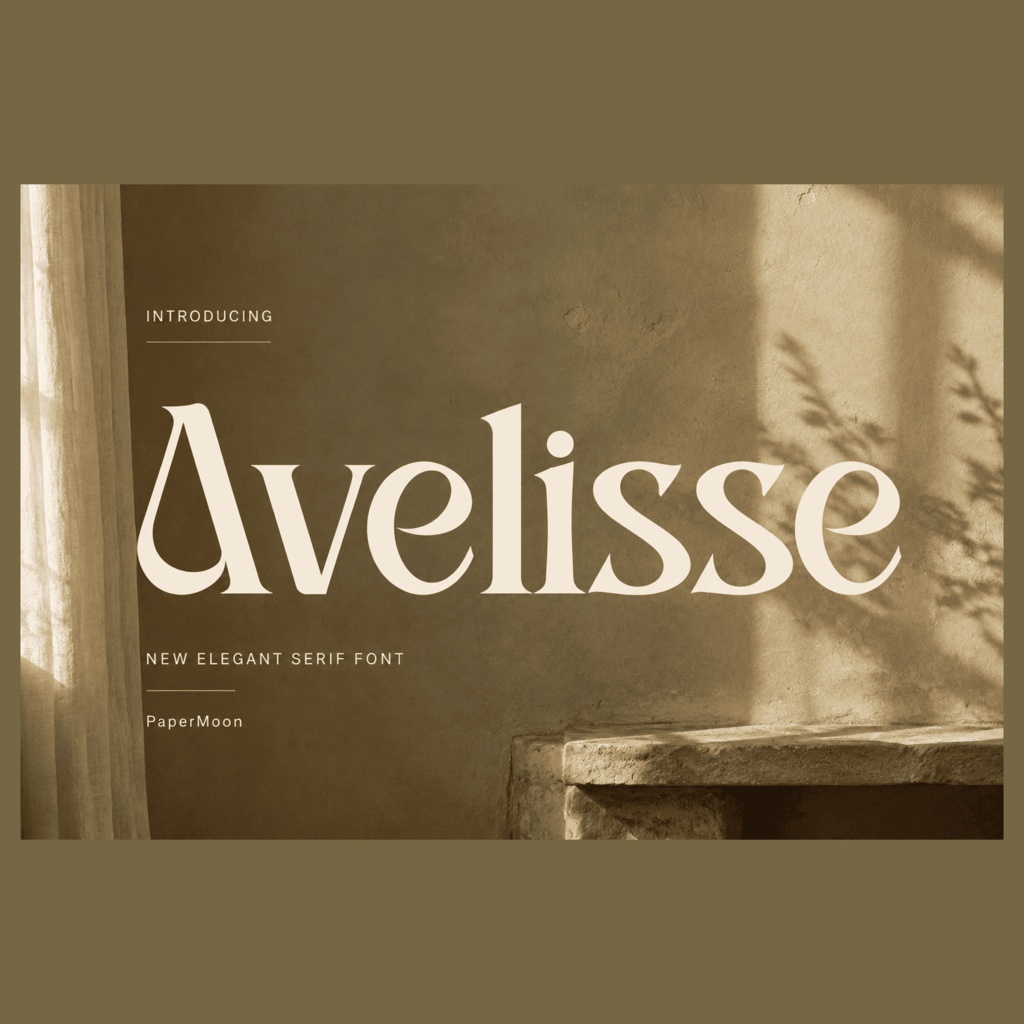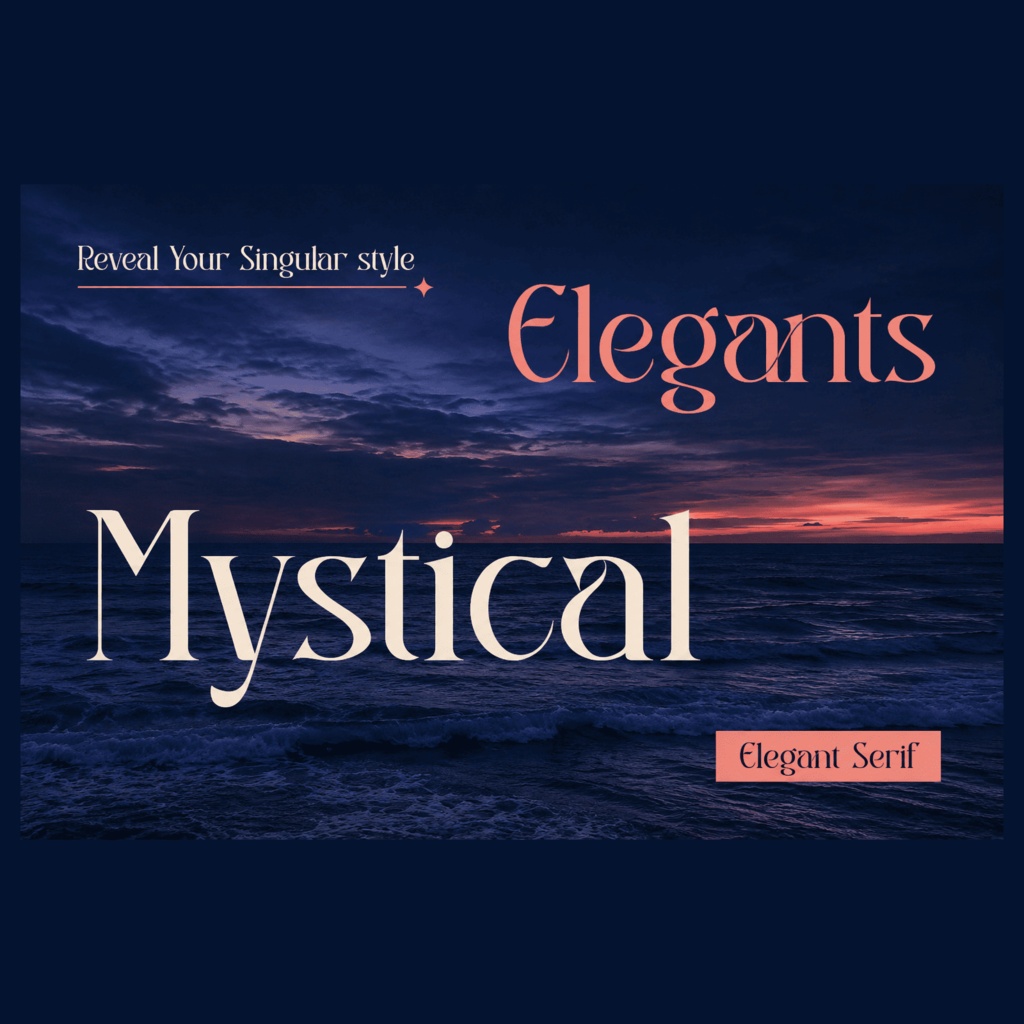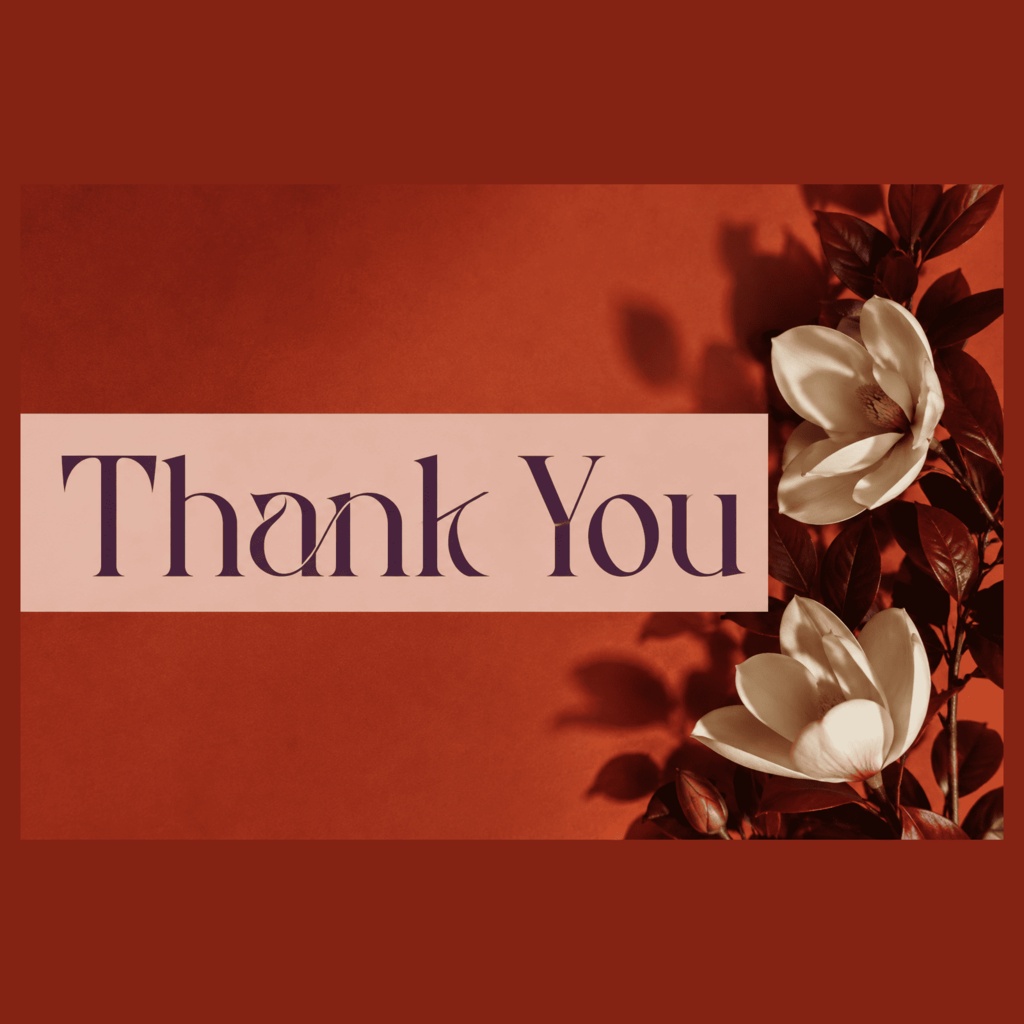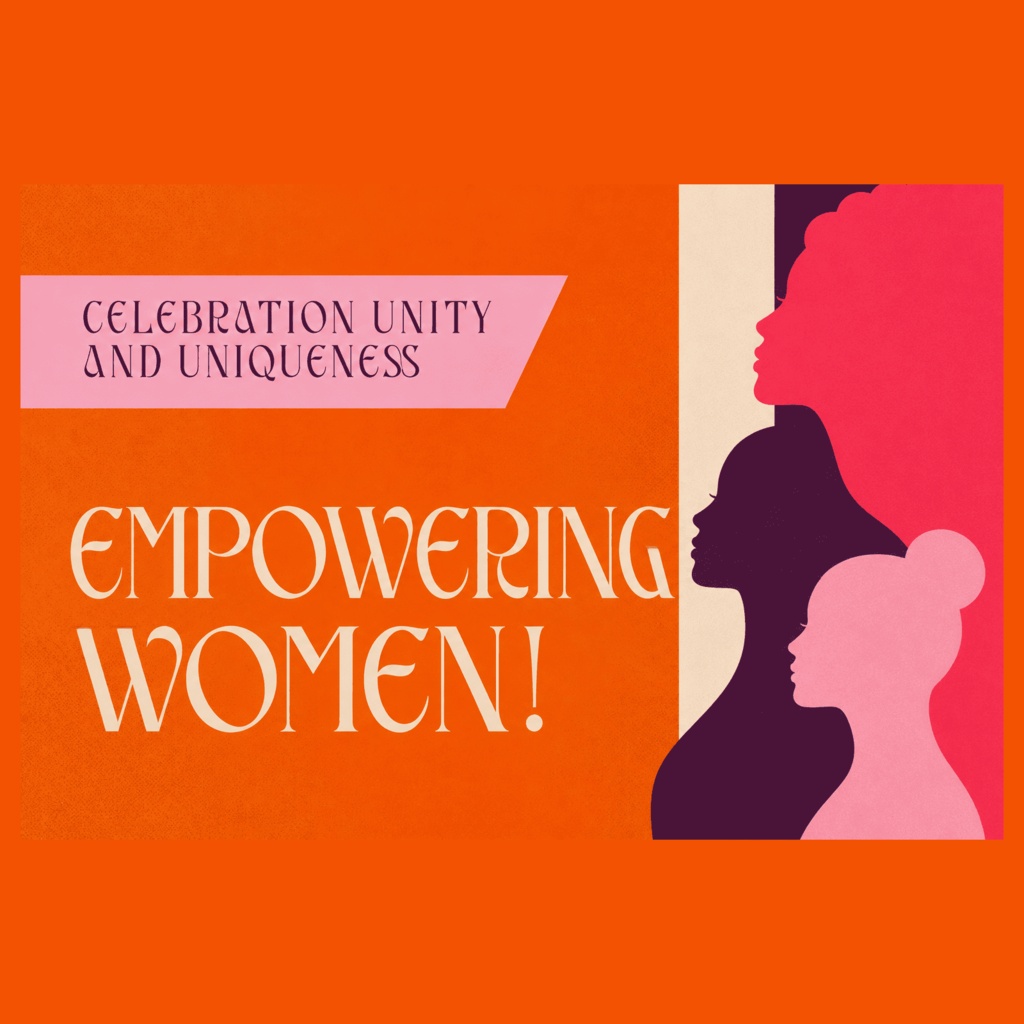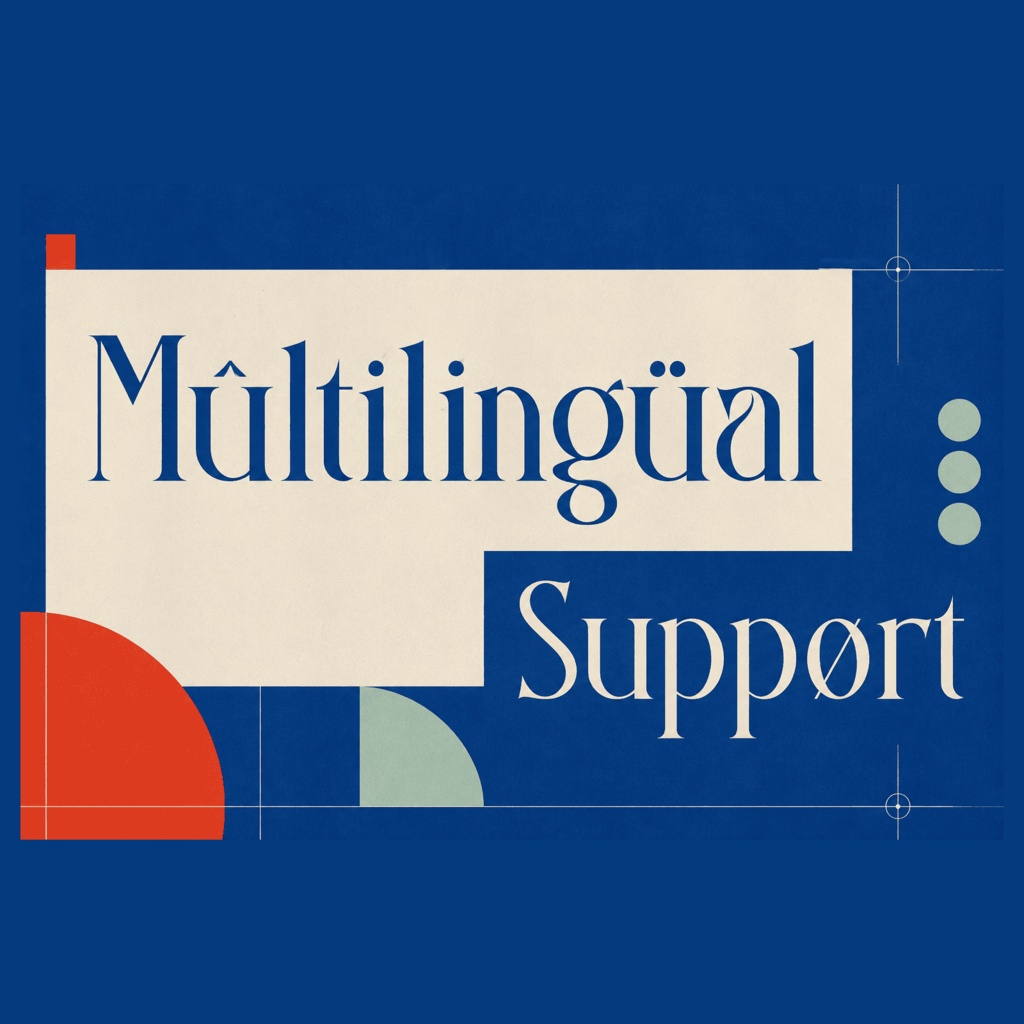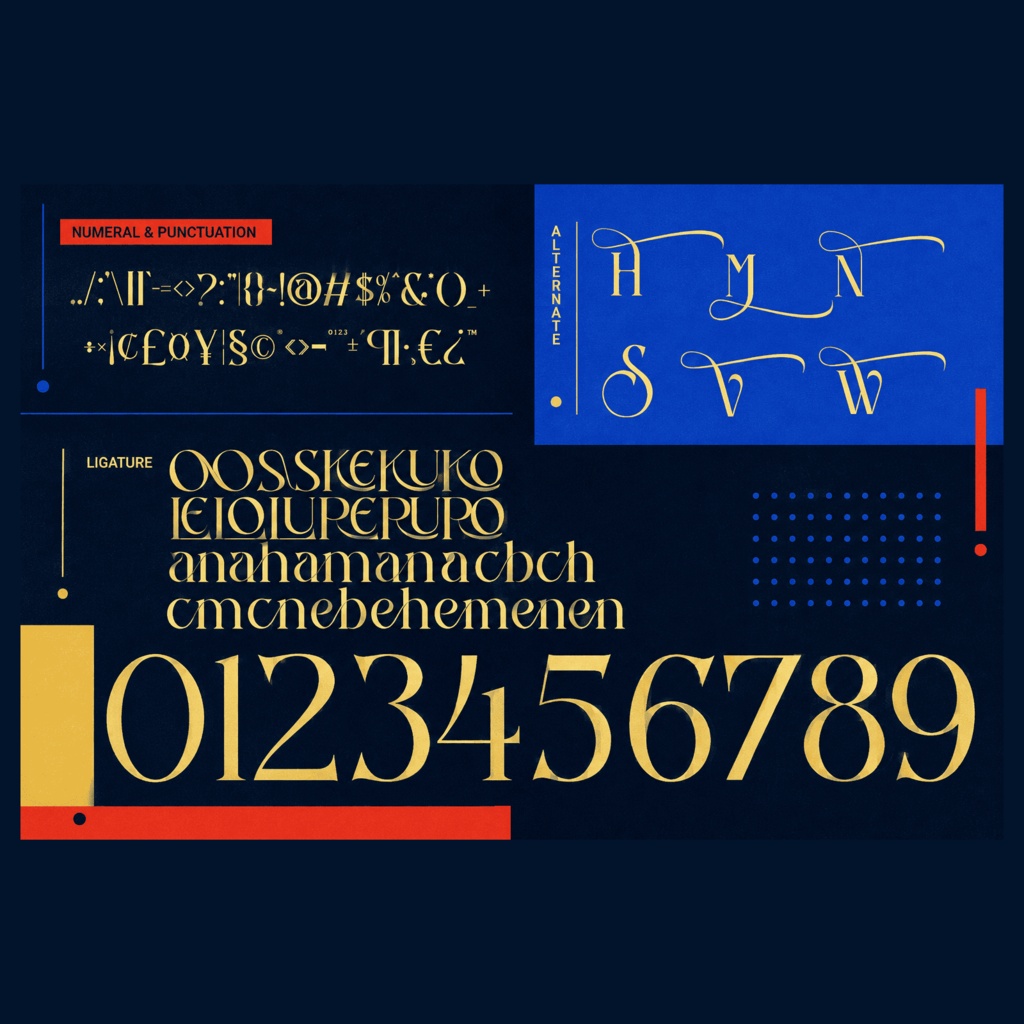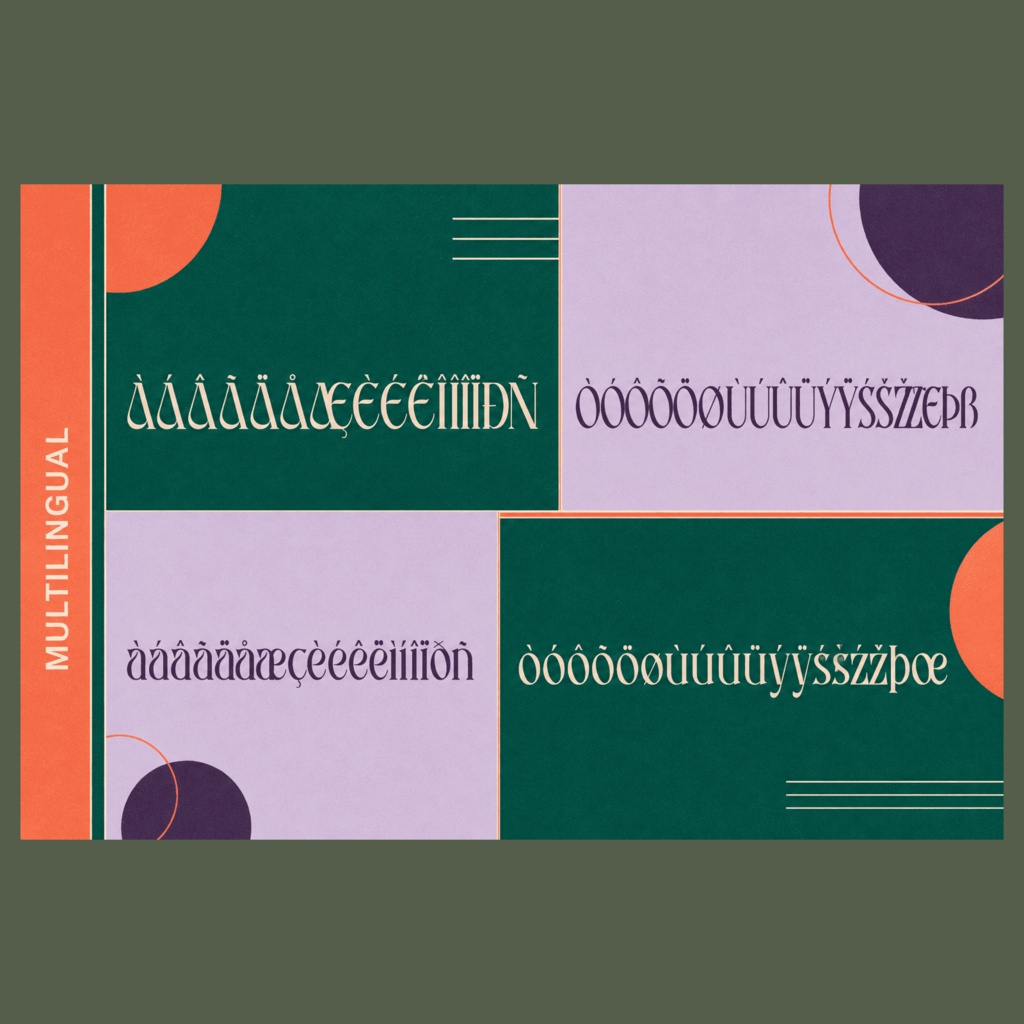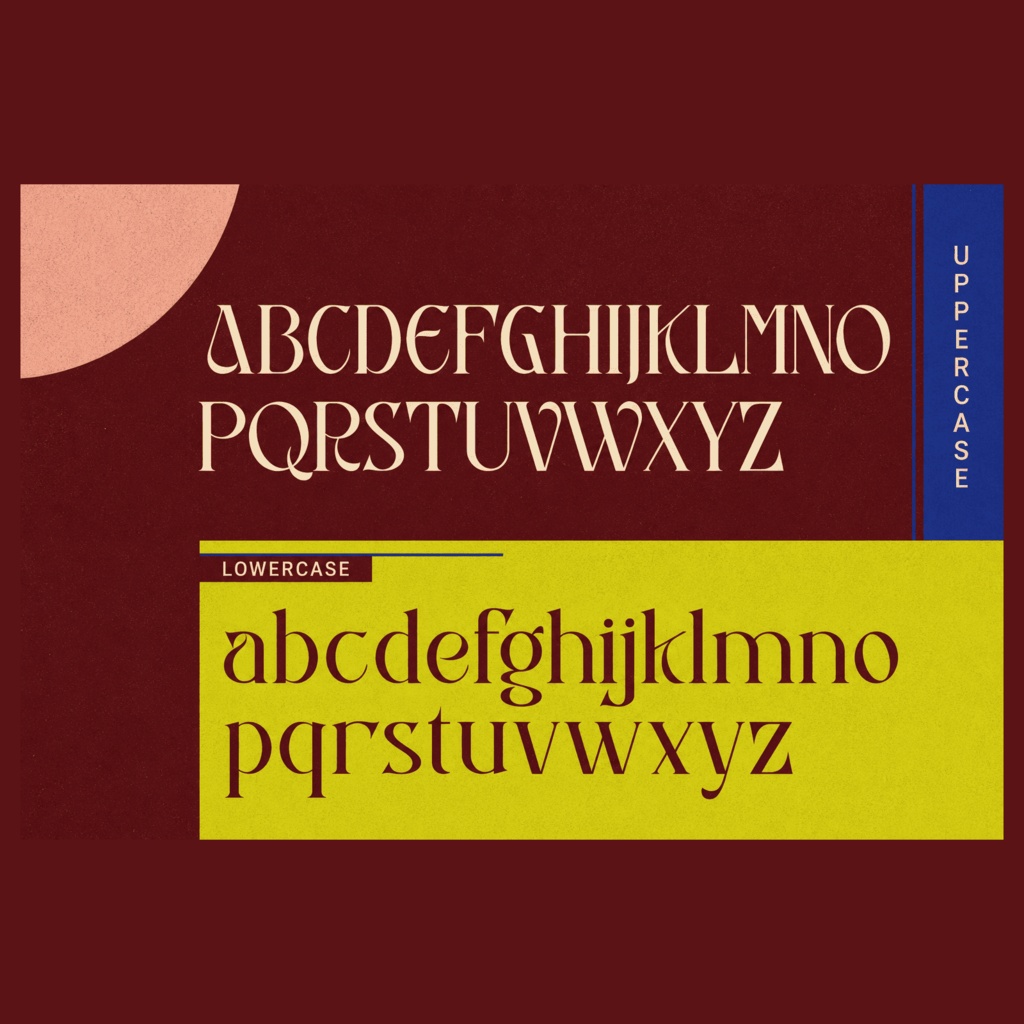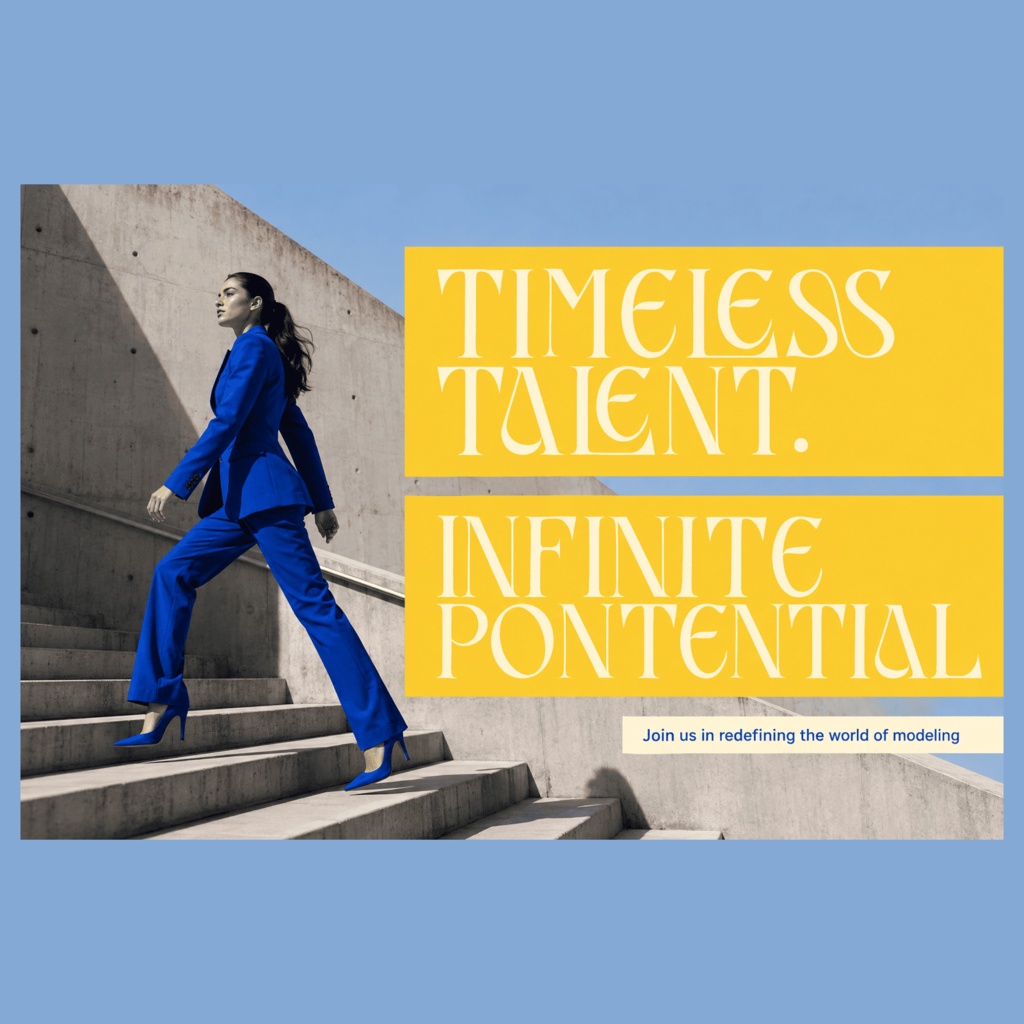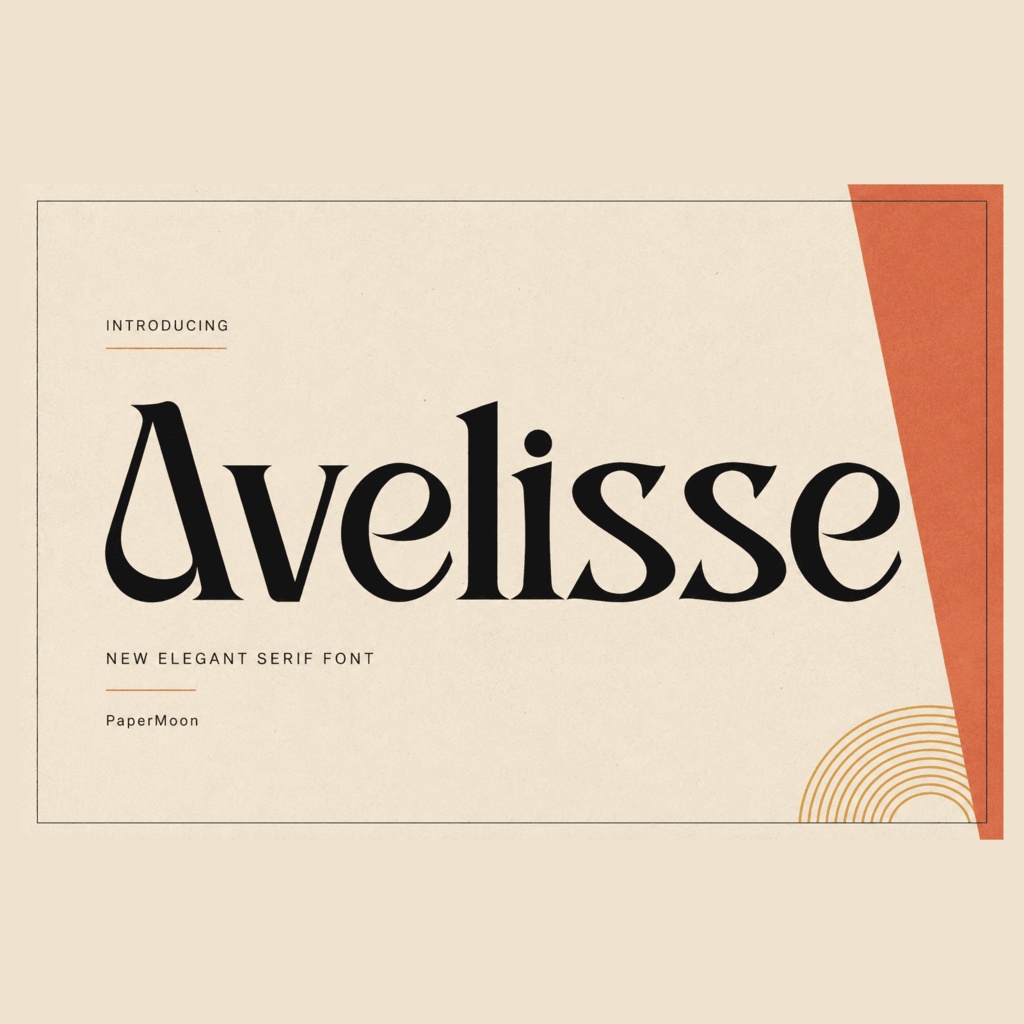
Avelisse | モダン・ラグジュアリー欧文セリフフォント | ロゴ・ブランディング向け
Avelisse(アヴェリス)は、高級ブランドのロゴ・ブランディング、エディトリアルデザイン、ウェディングの招待状などを想定した、モダン・ラグジュアリーの欧文セリフフォントです。シングルウェイトの Regular 1書体で、カスタム合字23組とスタイリスティック・オルタネイト6字を収録し、OTF / TTF / WOFF / WOFF2の4形式で同梱されます。クリーンでシャープなセリフと優美なカーブ、上質なコントラストが特徴で、プレミアムな印象を求める見出し・ロゴ・ブランド表現に適しています。 収録内容 - Avelisse Regular(単一ウェイト) - カスタム合字23組:OO, SS, KE, KU, KO, LE, LO, LU, RU, RO, RE と小文字ペア(ab, ah, am, an, cb, ch, cm, cn, eb, eh, em, en) - スタイリスティック・オルタネイト6字:H, M, N, S, V, W - OpenType GSUB / GPOS 対応(合字・オルタネイト・カーニング) - 形式:OTF / TTF(デスクトップ用)、WOFF / WOFF2(ウェブ用) 対応文字 ラテン文字のみ対応です。大文字A-Z、小文字a-z、数字、標準句読点を収録し、グリフ数はOTF / WOFF / WOFF2で229、TTFで230です。日本語(かな・漢字)、キリル文字、ギリシャ文字、アクセント付き欧文文字は含まれません。日本語テキストには対応していないため、和文フォントと組み合わせてご利用ください。 用途 * 高級ロゴ・ワードマーク、ブランドアイデンティティ * ファッション・ビューティー・ジュエリーのパッケージ * エディトリアル・雑誌の見出し * ウェディング招待状・イベント文具 * 高級ウェブサイトのヘッダー・SNSグラフィック * 同人誌の表紙・POP・グッズデザイン 形式 OTF / TTF(インストールしてデスクトップ・印刷で使用)/ WOFF / WOFF2(ウェブ、@font-face 用)。4形式とも同じ単一Regularマスターから生成されており、デスクトップとウェブで見た目は同一です。 対応環境 OTF・TTFはシステムフォントに対応したアプリで使用できます(Adobe Photoshop / Illustrator / InDesign、Canva、Figma、Affinity、Procreate、Microsoft Office など)。インストール後はアプリを再起動してください。OpenType機能(合字・オルタネイト)は、対応ソフトの Glyphs / OpenType パネルからアクセスします(対応状況はソフトにより異なります)。 利用許諾 商用ライセンス付きです。ロゴ・ブランディング、クライアントワーク、マーケティング、SNS、パッケージ、印刷物・POD商品などにご利用いただけます。フォントソフトウェア自体の再配布・再販・単体での共有は禁止です。ウェブ配信、SaaS、アプリへの埋め込み、放送、大規模な生産などについては、同梱ライセンスを事前にご確認ください。※掲載前に最終的なライセンス文面をご確認ください。 Copyright (c) 2026 PaperMoon. All rights reserved.